Skład tekstu – inicjały
Wpis Skład tekstu inicjały przedstawia charakterystykę dwóch rodzajów inicjałów: wpuszczonych i podniesionych. Pierwsze mają postać inicjału, który jest zagnieżdżony w tekście na wybraną wysokość wierszy, drugi jest ułożony na linii bazowej pisma i nie obłamuje tekstu. Zobaczmy jak się oba te inicjały prezentują na przykładach.
Inicjał wpuszczony jest to majuskuła, którą umieszczamy na początku rozdziału. Jest ona dużo większa niż reszta tekstu dziełowego i opada na wybraną głębokość kilku wierszy. Ustawienie inicjału możemy opracować w panelu sterowania, w opcjach formatowania akapitowego, i potem zapisać owo ustawienie w stylu akapitowym. Inicjałem możemy wyróżnić jedną lub kilka liter w tekście, a to zależy od koncepcji projektanta.
Inicjały wpuszczone używajmy wtedy, gdy rozdziały nie posiadają numerów lub tytułów. Taki inicjał w zupełności wystarczy, by dać czytelnikowi sygnał o rozpoczęciu nowej partii tekstu. Inicjały takie możemy używać w powieściach i w tekstach które nie posiadają wielostopniowej gradacji tytułów.
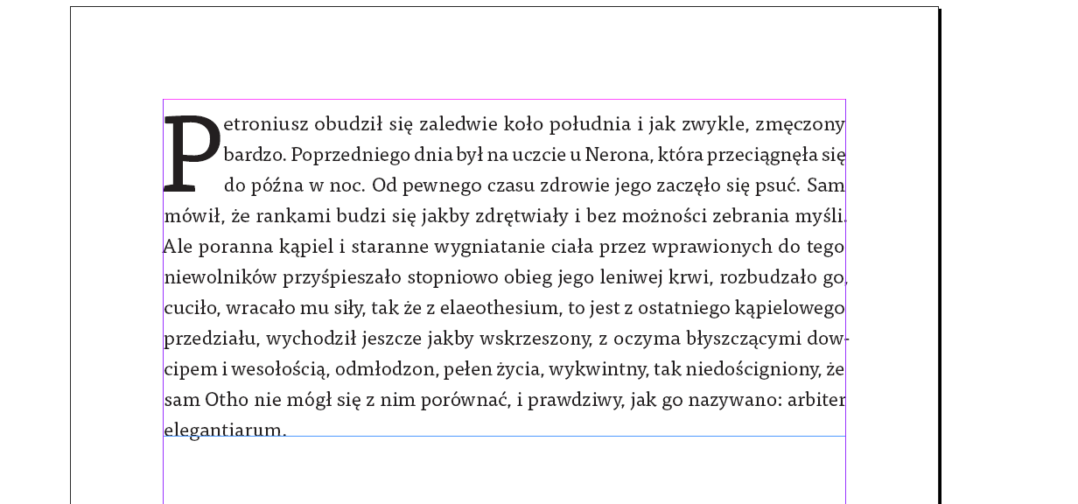
Inicjał podniesiony to powiększona pierwsza litera majuskułowa akapitu. Nie oblewamy jej tekstem, tak jak inicjał wpuszczony. Opiera się na linii bazowej pisma dziełowego pierwszego wiersza.
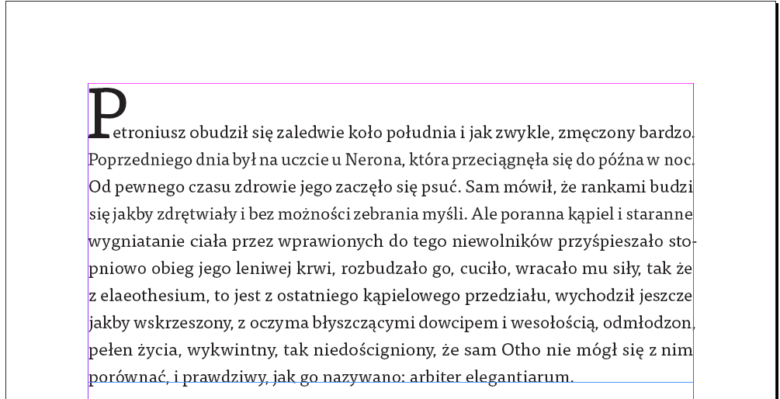
Inicjały podniesione, podobnie jak wpuszczone, najlepiej stosować w sytuacjach, gdy nagłówek nie zawiera numerów ani tytułów, a znakiem rozpoczęcia nowego rozdziału jest opuszczenie kolumny. Inicjałów tych używa się łatwiej, bo nie zakłócają wyglądu całego akapitu w sposób tak znaczący jak inicjały wpuszczone.